2023 年 37 种最佳轮廓字体(免费和高级)
已发表: 2023-10-04您是一名平面设计师,正在寻找完美的字体来提升您的项目吗? 别再犹豫了! 在这篇博文中,我们将探索 2023 年 37 种最佳轮廓字体,包括免费和高级选项。
现在,您可能想知道为什么轮廓字体值得考虑。 好吧,让我告诉你,轮廓字体由于其多功能性和现代审美,近年来变得越来越流行。
它们为任何设计增添了一丝精致和优雅,使其成为许多设计师的首选。
在我们深入讨论该列表之前,让我先分享一些有关本文的有趣统计数据和事实。 您是否知道正确选择字体可以显着影响项目的整体设计和可读性?
事实上,研究表明,使用正确的字体可以增强网站或任何其他设计的视觉吸引力和用户体验。 因此,选择正确的轮廓字体以使您的项目脱颖而出至关重要。
现在您知道为什么轮廓字体值得探索,让我们进入我们精心挑选的 2023 年 37 种最佳轮廓字体列表。
从时尚简约到大胆引人注目,我们收集了多种选择来满足每种设计风格和偏好。
因此,无论您是在制作徽标、网站还是任何其他图形设计项目,本文都可以帮助您找到完美的轮廓字体,为您的作品增添额外的精致感。 让我们开始吧!
最佳高级轮廓字体
希望为您的平面设计项目增添一丝优雅和现代感? 我们精选的最佳优质轮廓字体就是您的最佳选择。 这些独特的字体肯定会将您的设计提升到新的高度。 请务必在下面查看它们!
凯拉
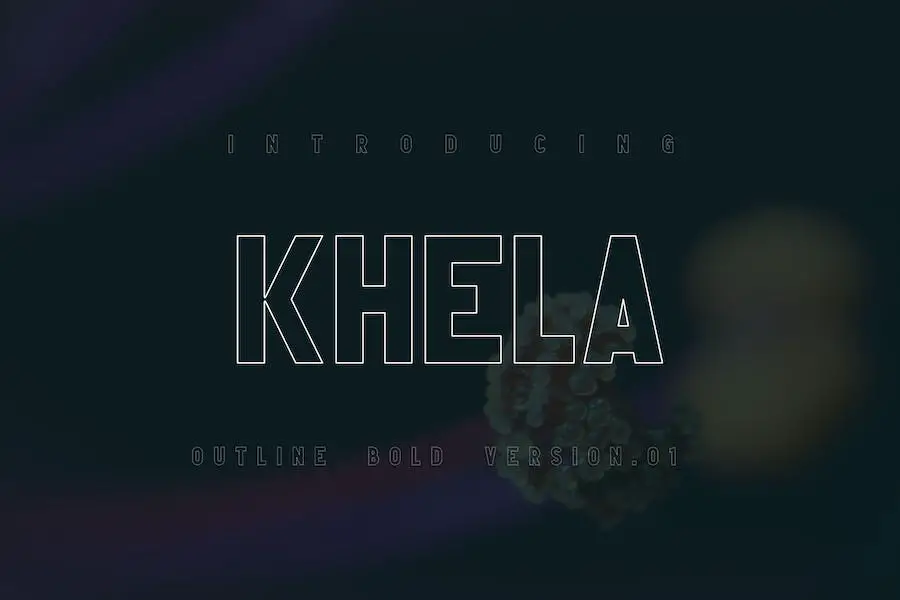
Khela 是一款令人惊叹的轮廓字体,非常适合想要增强项目设计的图形设计师。 这种字体以其干净、大胆的风格,为任何设计增添了现代和时尚的触感。
Khela的主要特点是其大胆的轮廓,使文字脱颖而出,产生强烈的视觉冲击力。 轮廓效果赋予字体独特且现代的外观,使其成为设计中徽标、标题和引人注目的元素的绝佳选择。
Khela 旨在吸引眼球,用途广泛,可用于数字和印刷项目。 它适用于各种背景,无论是鲜艳的颜色还是微妙的纹理。 这种字体一定会让您的设计流行并给观众留下持久的印象。
门廊
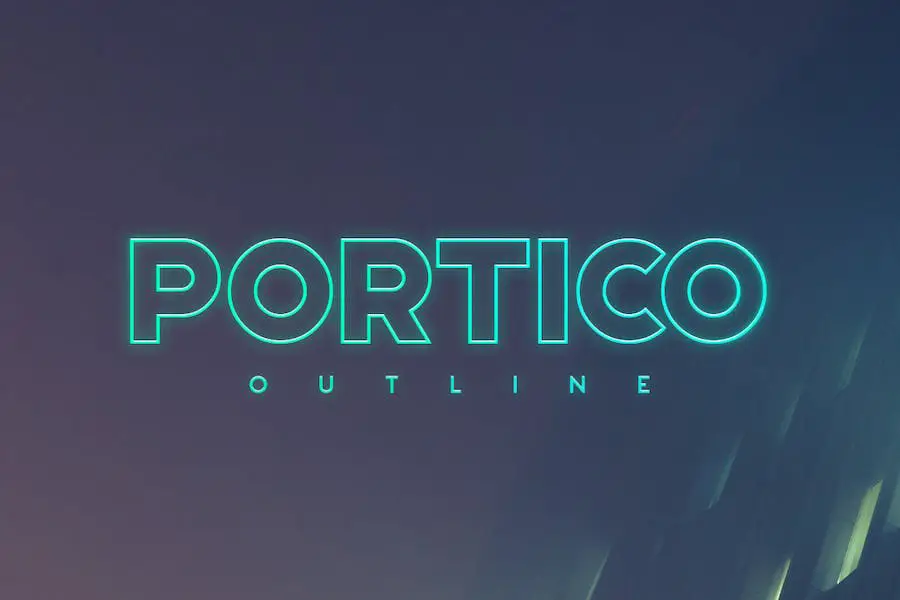
Portico 是一种粗体字体,非常适合为标题和突出的文本行增添冲击力。 凭借其时尚的轮廓设计,它可以毫不费力地与常规版本相得益彰,创造出具有视觉吸引力的组合。
此外,该字体充满活力的霓虹灯外观为任何项目增添了额外的风格。 无论您是在制作徽标还是海报,Portico 都一定会以其引人注目且微妙的设计来表达自己的观点。
吉布森斯
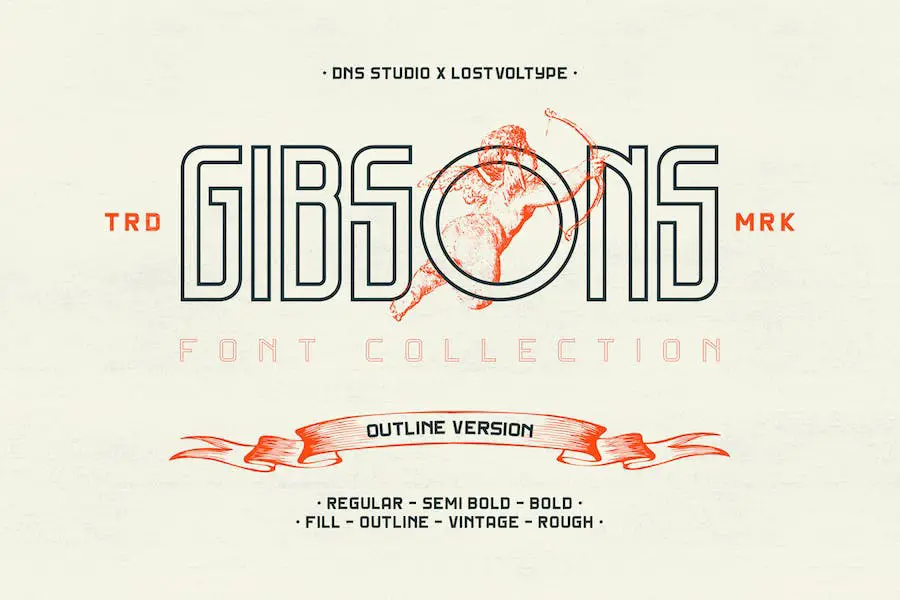
Gibsons 是一个很棒的字体集合,它将把您的图形设计项目提升到一个新的水平。 软件包中包含 20 种字体,您将有大量的选项可供选择。
字体有两种和三种粗细,范围从常规到半粗体和粗体。 最好的部分是什么? 每个权重都有四种样式:填充、轮廓、复古和粗糙,为您的设计提供更多多功能性。
Gibsons 的突出特点之一是字体如何完美搭配在一起。 高字体与短字体的组合创造了和谐而引人注目的设计。
展望
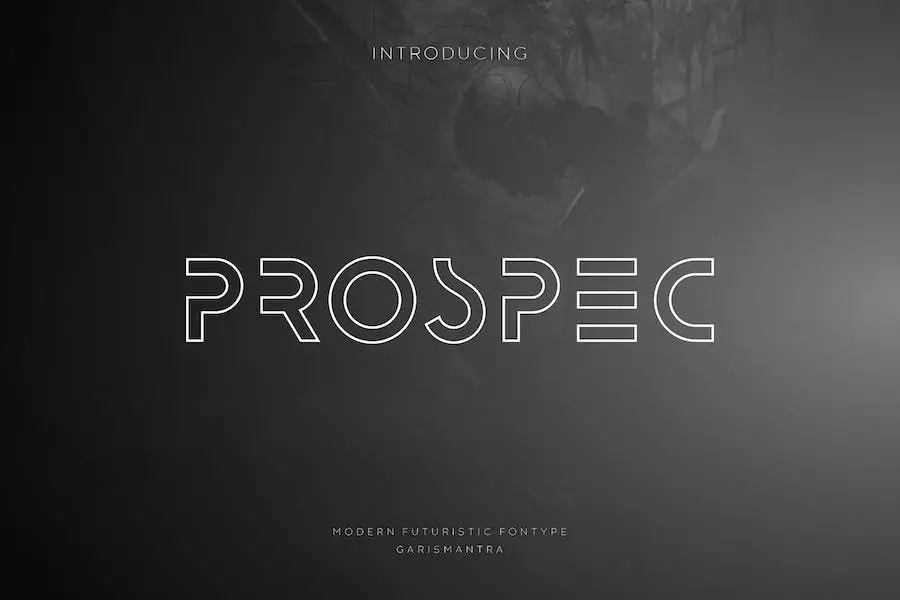
Prospec 是一种为您的设计项目带来现代和优雅风格的字体。 凭借其未来派的外观,这种字体非常适合网页设计、名片以及任何其他需要独特而复杂概念的东西。
它为未来的技术设计增添了时尚和现代的吸引力,使其成为图形设计师的必备字体。 无论您是创建网站还是制作名片,Prospec 都会以其时尚和未来主义的氛围将您的项目提升到一个新的水平。
不要错过使用这种字体提升您的设计的机会。
凯蒂胖子
Kitty Fat 是一款全新的手写字体,为您的设计带来大胆而有趣的元素。 Kitty Fat 的这款轮廓字体版本采用大画笔笔触,增添了额外的活力和创造力。
无论您是在从事儿童项目还是卡通风格的设计,这种大胆而流畅的轮廓字体都是完美的选择。
Kitty Fat 的突出特点之一是它的多功能性。 它可以在各种设计平台上无缝运行,包括 Google、Adobe、Word、Canva、Circuit、Figma,甚至可以用于纹身设计。 无论您在哪里需要使用它,Kitty Fat 都会为您的项目带来一丝现代感和魅力。
索雷尔
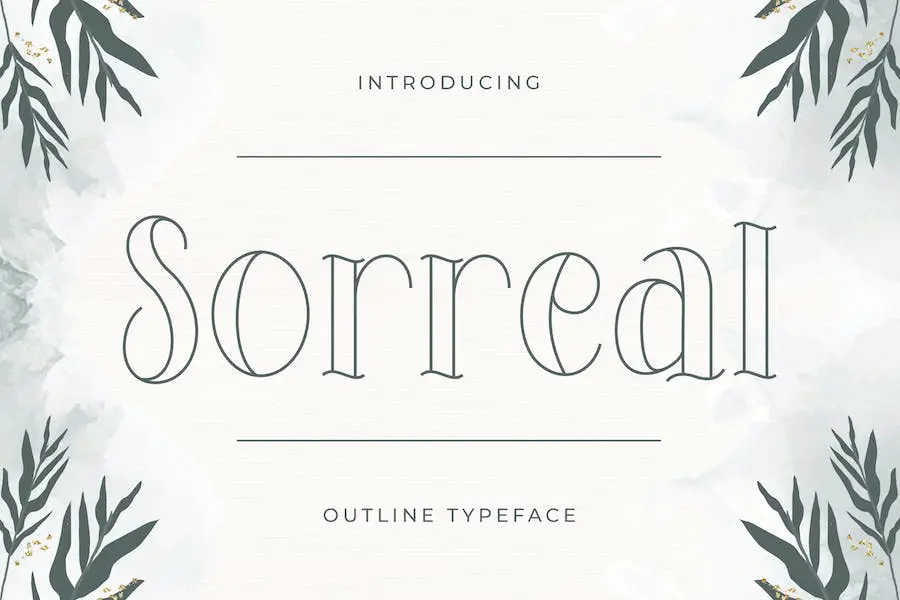
Soreal 是一种酷炫且友好的轮廓显示字体,非常适合增强您的图形设计项目。 无论您是设计徽标、婚礼请柬、标题还是标牌,Sorreal 简洁时尚的外观都会为您的作品增添独特的触感。
它用途广泛,适用于信头、标签、新闻文章、海报和徽章。 有了Sorreal,就有无限的可能性。
肯巴拉辛塔
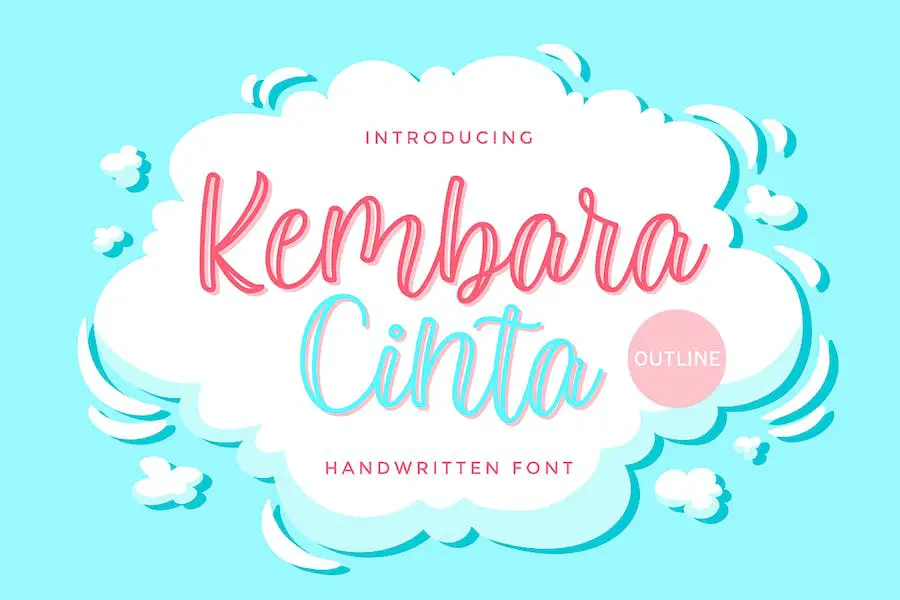
Kembara Cinta 是一种令人惊叹的新字体,名为“Outline”,具有现代手写书法风格。 凭借其装饰性字符和俏皮的基线,该字体非常适合为您的设计项目增添优雅的触感。
无论您是在创建邀请函、贺卡、品牌材料、名片、引言还是海报,这种字体都会将您的设计提升到全新的美感水平。
Kembara Cinta 的突出特点之一是其独特且引人注目的书法风格。 这些字母经过精心制作,具有流畅和艺术的外观,为任何项目增添了一丝优雅。
潘多拉
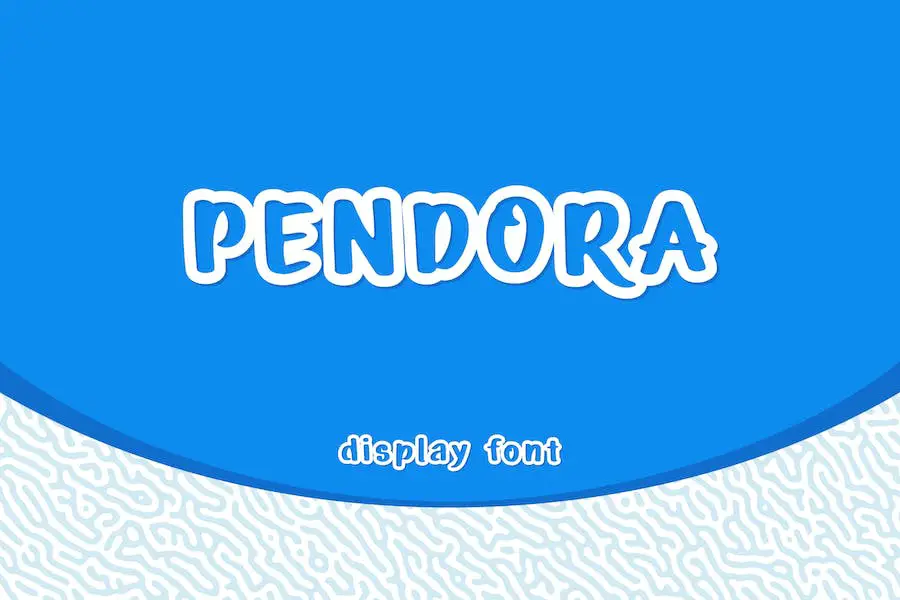
Pendora 是一款令人惊叹的轮廓漫画显示字体,可为您的项目增添手工制作的感觉。 无论您是在制作漫画、海报、卡片、书名,甚至是新闻标题,Pendora 都是完美的选择。 它用途广泛,可用于任何规模的工作,使其成为寻求增强设计的图形设计师的必备工具。
这种字体具有独特的魅力,将使您的项目脱颖而出。 它的轮廓样式增加了深度和维度,给您的文本带来俏皮和艺术的外观。 使用 Pendora,您可以轻松创建引人注目的横幅、传单和文具。
Pendora 的一大优点是它的多功能性。 它可以用于不同的环境和不同的目的。 无论您想要大胆、引人注目的设计,还是更微妙、精致的外观,Pendora 都能满足您的需求。
光谱仪
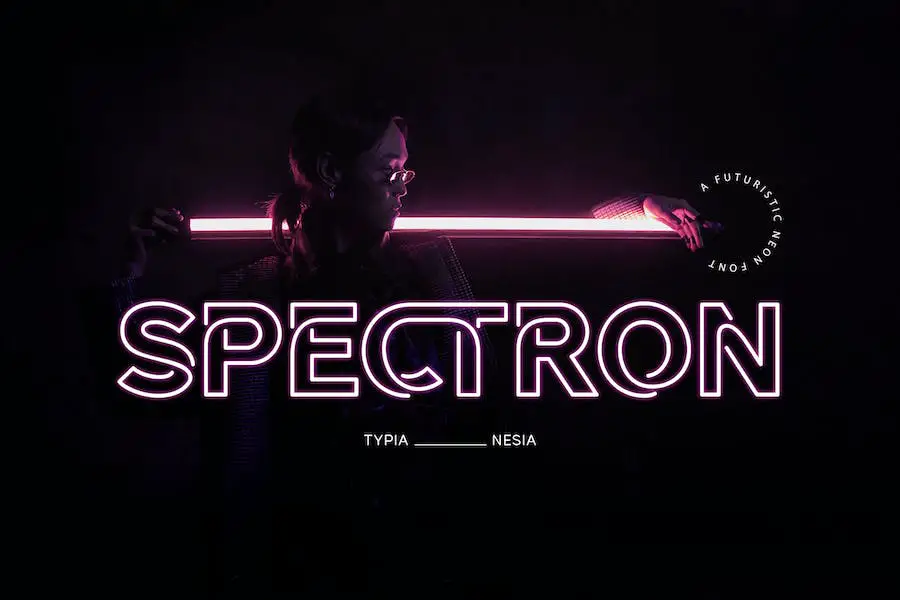
Spectron 是一款令人印象深刻的霓虹灯显示字体,是所有图形设计师的必备工具。 这种字体用途广泛,可用于各种项目,包括徽标品牌、编辑设计、文具设计等。
凭借其独特而现代的设计,Spectron 非常适合为任何设计增添复古气息。 无论您是在制作音乐海报、博客设计还是特别活动邀请函,此字体都会将您的项目提升到一个新的水平。
对于那些希望通过时尚、引人注目的字体来增强设计的人来说,Spectron 是完美的选择。
飞口
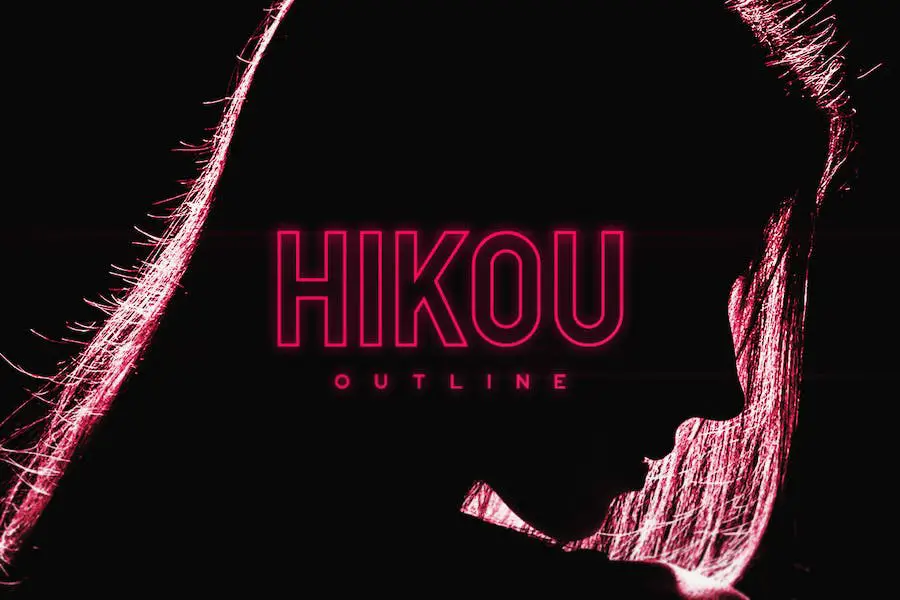
Hikou 是一种轮廓字体,非常适合希望增强项目设计的图形设计师。 当与霓虹色和大尺寸一起使用时,这种字体特别闪亮。
它提供了多种多语言大写字母、数字和标点符号,使设计师能够用各种语言表达他们的创造力。 有了 Hikou,您的设计将真正脱颖而出并做出大胆的声明。
美元概要
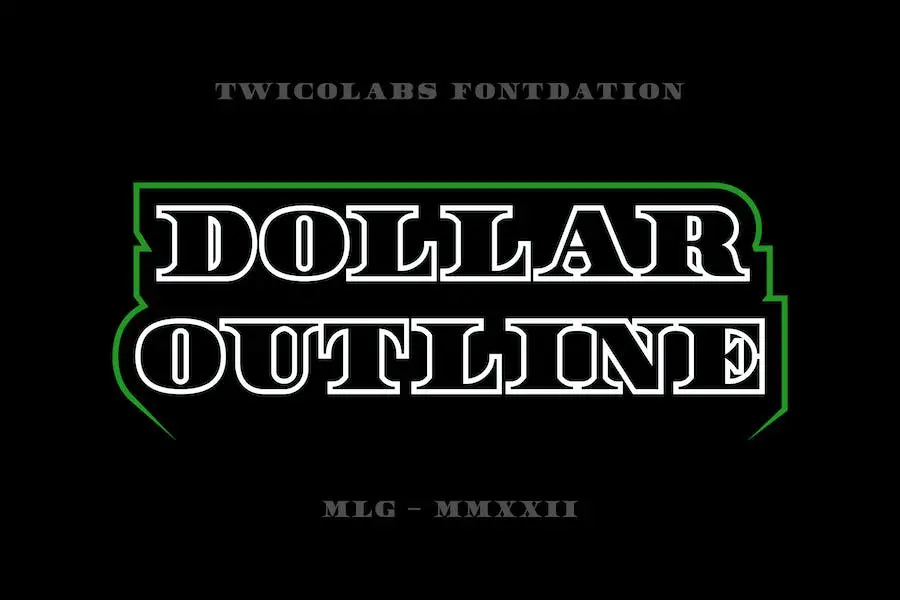
Dollar Outline 是 Dollar 系列字体的独特补充。 受到钞票的启发,它采用全大写印刷衬线风格,为任何设计项目增添了经典和复古的气息。
无论您是在制作复古海报还是怀旧品牌宣传活动,这种字体一定会提升您的项目。 立即使用 Dollar Outline,为您的设计带来一丝权威和优雅。
贝利格罗
Belligro 是一款华丽的脚本字体,可为任何创意项目增添一丝个性。 要充分体验其美感,最好使用 Adobe Illustrator、Adobe Photoshop CC、Adobe InDesign 或 CorelDraw 等支持 OpenType 功能和 Glyphs 面板的设计程序。
Belligro 凭借其甜美而令人惊叹的外观,非常适合各种项目。 无论您是在制作徽标和品牌、邀请函、文具、婚礼设计、社交媒体帖子、广告、产品包装还是标签,这种字体都会将您的工作提升到一个新的水平。
通过将 Belligro 融入您的设计中,您将能够获得独特且个性化的感觉。 其美丽的脚本风格将吸引您的观众并使您的项目脱颖而出。 尝试一下 Belligro,看看它将您的设计变成真正特别的东西。
莫林
Morline 是一款经典的线条字体,从手工刻字中汲取灵感。 这种即用型字体非常适合为现代设计、书籍封面、海报、传单等增添复古气息。
其永恒的风格和多功能性使其成为任何平面设计师工具包的绝佳补充。 借助 Morline,您可以轻松提升项目设计并创造出具有视觉吸引力的独特外观。
因此,如果您正在寻找一种将经典魅力与现代风格相结合的字体,Morline 绝对值得一试。
贝卡克
Becak 是一种独特的字体,提供大写和小写字母,以及标点符号、符号、数字、连字和多语言支持。 凭借其俏皮和大胆的风格,它可以让您创造出有趣和新鲜的设计。
该字体具有圆角,并提供两种样式:实心和轮廓。 这使其非常适合各种设计目的,例如徽标设计、儿童 T 恤、生日贺卡、书籍封面、杂志、传单、报价、包装等。
利奥伦坦大纲
Liorentin Outline 是平面设计师必备的字体。 这是一个令人惊叹的脚本,可为任何设计项目增添个人风格。 此字体附带 OpenType 功能和字形面板,因此请确保您有 Adobe Illustrator 或 Photoshop 等程序来访问所有不同的变体。
这种字体具有俏皮和甜美的外观,将使您的设计脱颖而出。 它非常适合徽标、品牌、摄影、社交媒体帖子、广告等。
Liorentin Outline 字体为您的作品带来手写风格,非常适合邀请函、产品包装和特别活动。
拉利克塞特
Ralixet 是一种大胆而真实的显示字体,称为 It-Outline Font – Modern Font。 它非常适合各种品牌项目,包括徽标、T 恤印刷和令人兴奋的电子竞技世界。
这种字体脱颖而出,为任何设计增添现代感。 您可以在不同的环境中自信地使用它,使您的项目在视觉上有吸引力且专业。
诺斯特罗莫
Nostromo 是一种多功能且具有未来感的字体,可以增强任何图形项目的设计。 这种字体具有各种粗细和样式以及某些字母的样式替代方案,提供了无限的可能性。
它还提供多语言支持,包括基本的拉丁语、西欧、中欧和东南欧字符,确保您可以满足多种语言的需求。
此外,Nostromo 包含数字和标点符号,使其成为图形设计师全面且用户友好的字体选择。
大纲
Outline 是一种专为标题和标题设计的新显示字体,使您的版式脱颖而出。 它非常适合添加您的个人风格并创造引人注目的头条新闻。
Outline 具有独特而现代的感觉,可让您在任何项目中展示您的主要想法。 享受自由表达您的创造力并用这种字体给人留下深刻的印象。
鲍伦斯
Baurems 是一种多功能字体,可以提升您的设计项目。 它是海报设计、徽标、品牌和街头服饰的完美选择。 受到 90 年代和 20 世纪的涂鸦和混合媒体视觉效果的启发,Baurems 捕捉到了这一艺术运动的精髓。
无论您是创建时尚品牌还是为您的设计添加前卫风格,Baurems 都是适合您的字体。 其大胆的轮廓风格为任何项目增添了独特和动态的风格。
让 Baurems 发挥您的创造力,让您的设计在人群中脱颖而出。 与 Baurems 一起拥抱城市艺术精神。